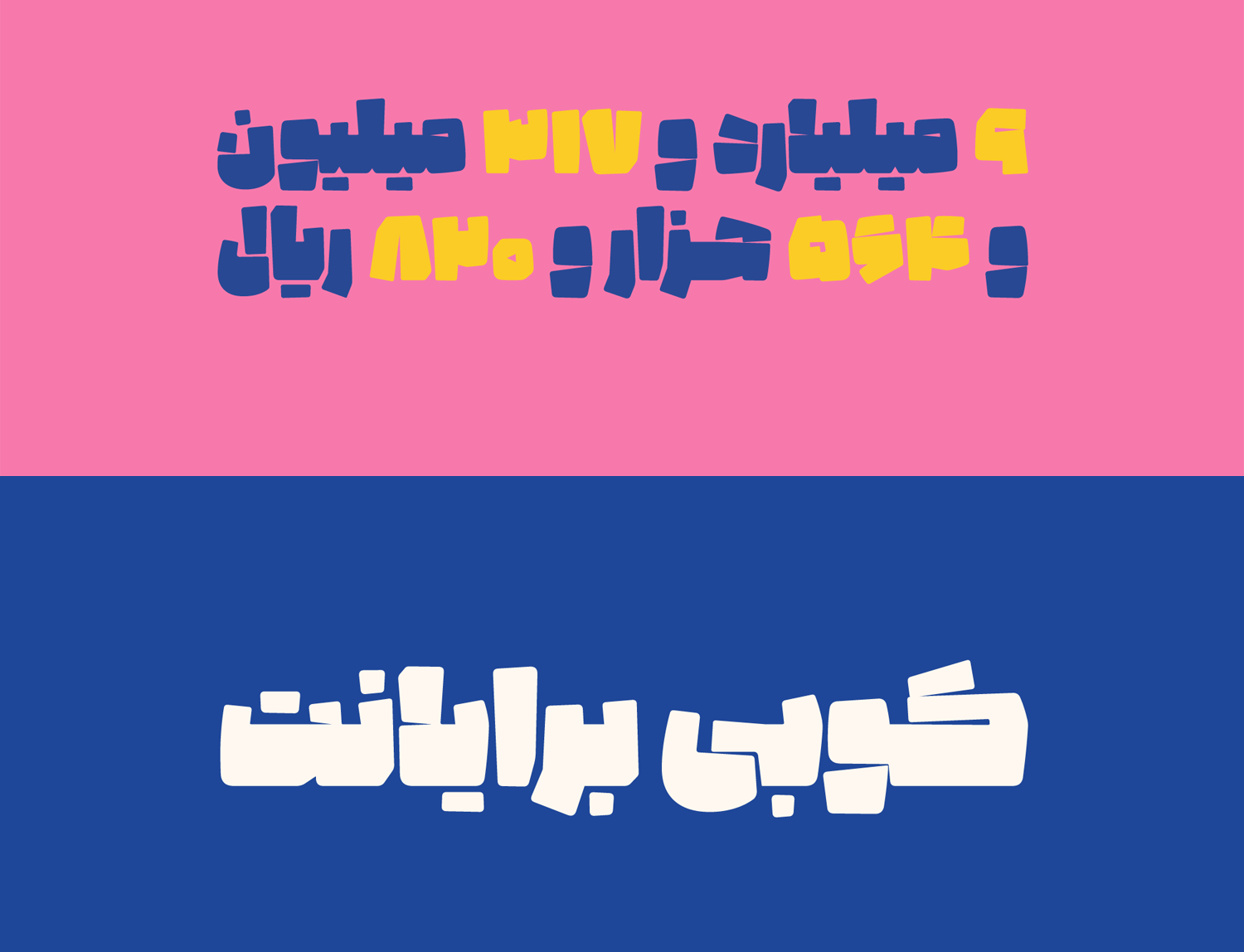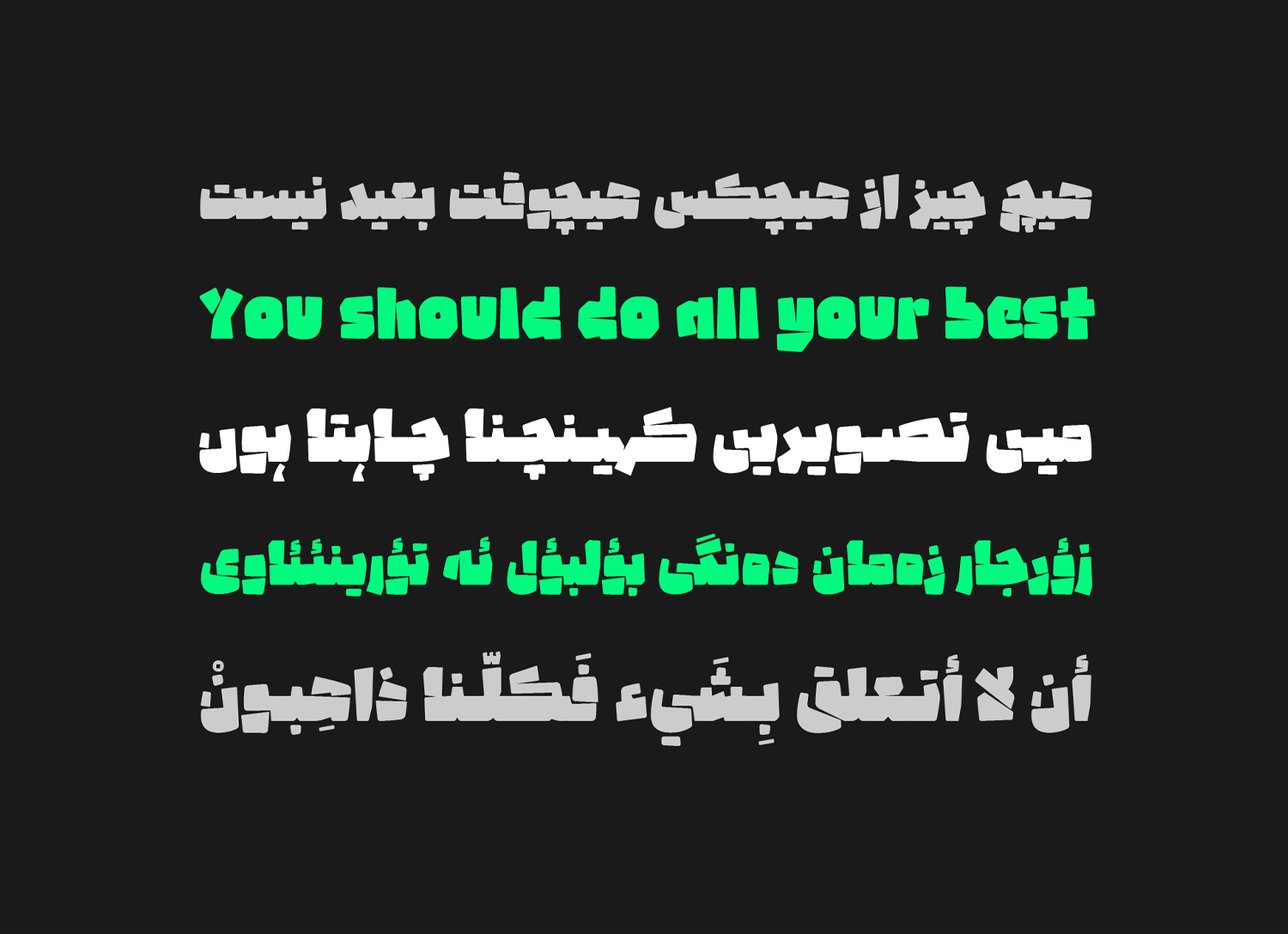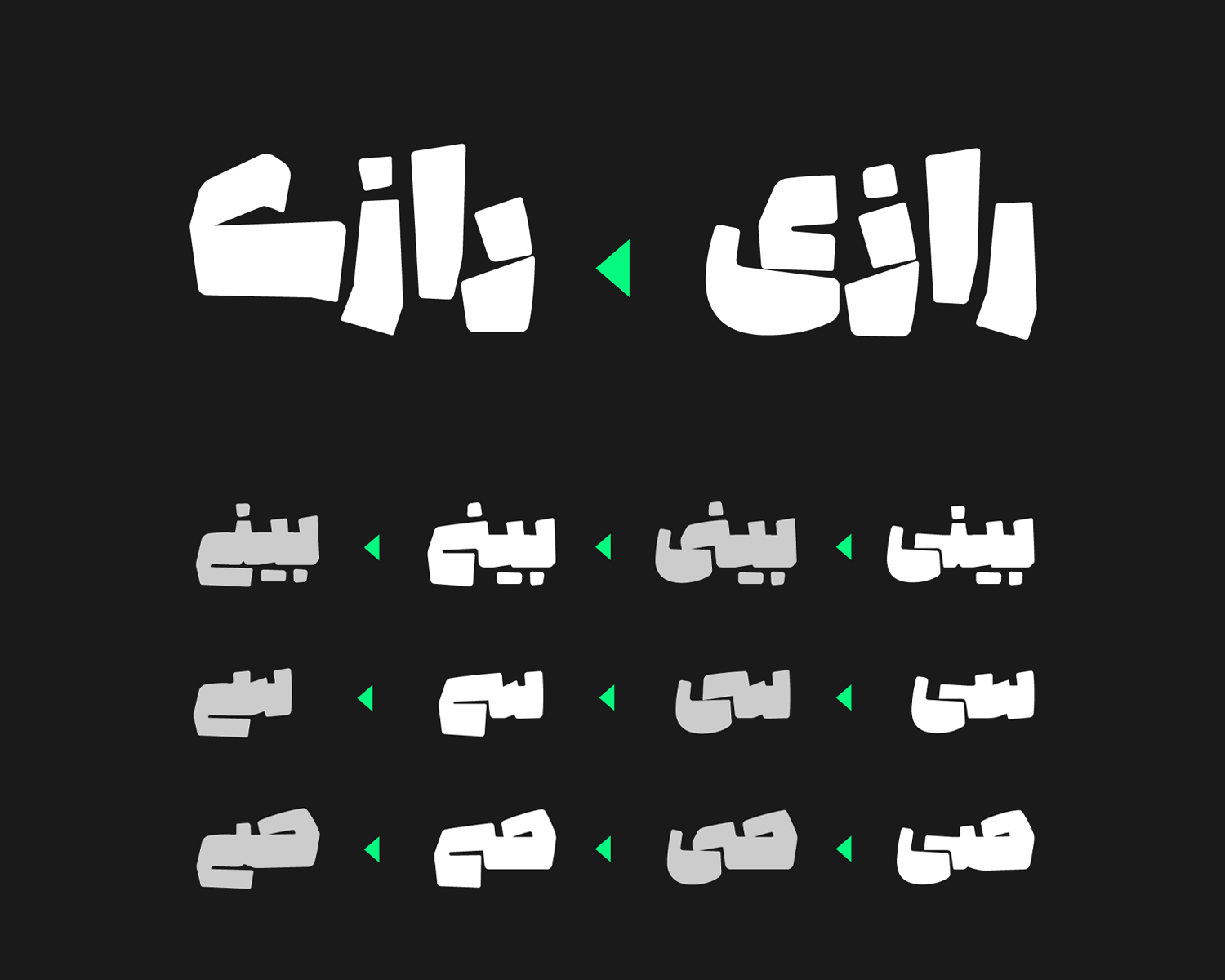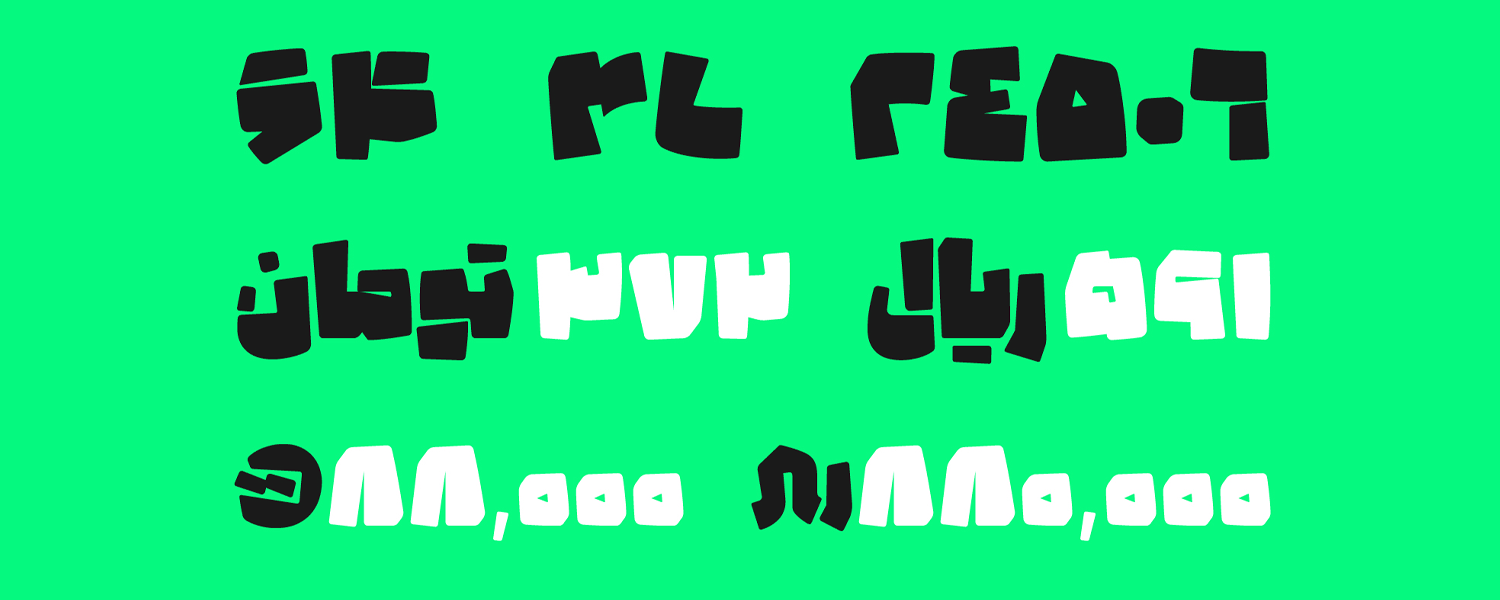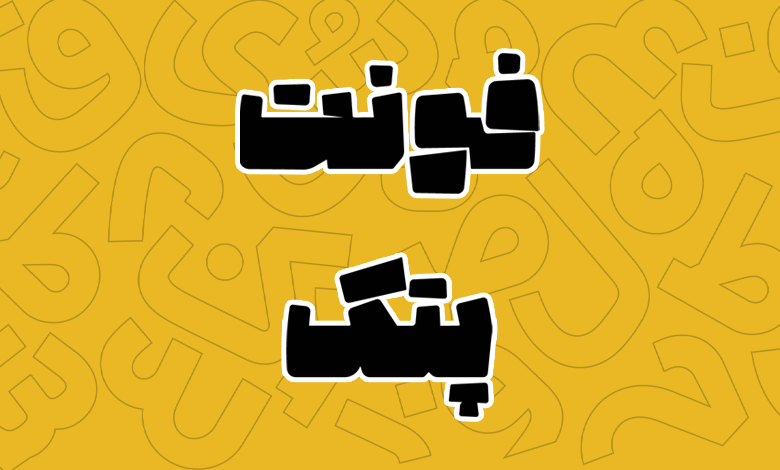
فونت پتک (Potk)
فونت پتک (به انگلیسی: Potk) در دنیای پر تلاطم خطوط فارسی، درست در جایی که نیاز به فونتی برای جلب توجه مخاطب داریم ظاهر شده است. این فونت فانتزی که از وزن سیاه (Black) پشتیبانی میکند، دارای ساختاری هندسی و نمایشی است که نهتنها برای عناوین کوتاه و تیترها کاربرد دارد، بلکه با الهام از ضربات قدرتمند پتک بر آهن گداخته، شکلی نو و خلاقانه به حروف میبخشد.
اگر به دنبال فونتی نمایشی و هندسی هستید که سیاهی حداکثری را در خود داشته باشد و در عینحال جلوهای فانتزی به حروف ببخشد از فونت پتک استفاده کنید. مهدی ارشادی این قلم را برای پروژههای گرافیکی جسورانه طراحی کرده است. فونت پتک رایگان نیست و در قالب یک وزن سیاه قابل خریداری است.
در ادامه این نوشته از فونتچی، به نقد و بررسی کامل فونت پتک خواهیم پرداخت؛ قلمی با وزن فوق سنگین و نمایشی که پیش از این نمونههای مشابه این قلم را در صفحات فونت صنعت و فونت تهمتن بررسی کردهایم.
بررسی و دانلود فونت پتک (Potk)
حروف فارسی را زیر ضربات بیرحم یک پتک، تصور کنید که تغییر شکل داده و هرکدام شخصیت خاص خود را میگیرند. در برخی لبهها از خوردگیهای پتک ظاهری نرم میگیرند، برخی دیگر طاقت ضربات را نداشته و با شکستگیها و شکافهای ناگهانی خود را نشان میدهند و برخی دیگر با فرورفتگیهای خاص خود، با تحمل ضربات خودنمایی میکنند.
فونت پتک دقیقا با چنین رویکردی ساخته شده است. ساختار هندسی آن، با کاهش فضای بین حروف (کرنینگ فشرده)، برهمزدن یکنواختی ضخامتها و تغییرات تصادفی در اندازهها، یک فونت فانتزی سنگین میسازد که برای عناوین کوتاه، عکس نوشتهها و لوگوتایپها بینظیر است.
در دنیای فونتها باید واقعبین باشیم؛ هیچ فونتی کامل نیست و این فونت هم مثل هر فونت دیگری برای استفاده در پاراگرافهای طولانی مناسب نیست. اما وقتی صحبت از تیترها، پوسترها، کاور آلبومها و استوریهای اینستاگرام به میان آید، مانند یک چکش بر آهن داغ عمل میکند.
وجود اعراب متناسب با جثههای متفاوت و نقطههای متمایز در حروف (مانند دو شکل جایگزین برای «ر»، «ک»، «ه» و «ه»)، جلوه نمایشی را تقویت میکند. وجود ترکیبات اختیاری و کشیدگیها (لیگاتورها) دست طراحان را برای خلق عباراتی کاملا سفارشی بازتر میکند. خلاقیت در جزئیات، مانند الهام از کوبیدن پتک بر سنگ یا سیمان، پتک را به یک ابزار هنری تبدیل کرده که هر بار استفاده، حس تازگی میدهد.
فونت کولاک و فونت بلوک از دیگر قلمهای طراحی شده با همین سبک هستند که وزن فوق سنگین و ضخامت زیادی دارند. از این قلمها میتوانید برای طراحی در تبلیغات استفاده کنید که خصوصا نیاز است نامی از برند برده شود.
یا اینکه با توجه به ساختار قلم که الهام گرفته از آهن و آهنگری است، در طراحی تابلوهای صنعتی در سردر فروشگاهها، کارگاهها و هر واحدی که محصول یا خدماتی دارد که قدرت و مقاومت جزو ارکان اصلی آن است استفاده کنید.
ویژگیهای فنی و وزن فونت پتک
فونت پتک در یک وزن سنگین ساخته شده، که با سیاهی حداکثریاش، برای فونت سنگین سیاه فارسی ایدهآل است. پشتیبانی از زبانهای فارسی، عربی، کردی، اردو و انگلیسی، آن را به گزینهای مناسب برای کارهای چندزبانه تبدیل کرده است. خصوصا در موضوعات تبلیغاتی که بیشتر کاربرد دارد. این فونت با پشتیبانی از اعداد فارسی و حروف جایگزین (Alternates) امکان خلق بهتر کارهای گرافیکی را فراهم کرده است.
در طراحی کلیه حروف با ضخامتی متغیر مواجه هستیم که در اثر ضربات پتک ایجاد شده و انتظار هم میرود برخی حروف شاهد خطوطی صاف و در برخی دیگر شاهد خطوط مورب باشیم که در اثر این ضربات وارد شدهاند.
کوبیدن پُتک روی هر چیز به تغییر ریخت اجسام میانجامد و با داشتن ایدهای مناسب میتوان آن را به شکلی خاص بدل کرد. تفاوتی نمیکند چه چیز زیر ضربات پُتک قرار دارد؛ نحوهی برخورد و شدت ضربهها تعیین کننده است. آهن گداخته، سنگ معادن، بلوکهای سیمانی و حتی حروف قابلیت تغییر شکل دارند.
مهدی ارشادی؛ طراح قلم پتک.
این قلم فقط دارای یک وزن سیاه Black است؛ اما با این حال ضخامتی که حروف دارند سیاهتر به نظر میرسند. هرچه هم سایز فونت را درشتتر کنید، با توجه به ترکها، نرمی و شکافها، بیشتر دیده شده و جلب توجه خواهند کرد.
پشتیبانی از ۵ زبان مختلف
فونت فارسی پتک محدود به این زبان نیست و با زمانی که روی طراحی و توسعه آن با دید آهنگری صرف شده، توسعه دهنده صبر زیادی را به خرج داده تا نتیجه نهایی را در قالب ۵ زبان مختلف در اختیار داشته باشید.
عربی، انگلیسی، اردو و کردی از دیگر زبانهای پشتیبانی شده هستند. ساختار هر زبان به شکل استاندارد پیادهسازی شده است. بهطوری که اعراب و کاراکترهای تزئینی در همنشینی استانداردی با حروف قرار دارند. علاوهبر این حروف جایگزین، برای زبانهای برپایه رسمخط فارسی قابل استفاده است.
تغییراتی مثل کمشدن فضای بین حروف و چشمیها، برهمزدن یکنواختی در ضخامتها، شکستگیهای اتفاقی در اثر ضربات پتک و تغییر در اندازهها فضای متفاوتی را در فونت پتک برای تمامی زبانها بهوجود آورده است که با دقت به تصویر بالا میتوان این موضوع را هم متوجه شد.
ترکیبات و حروف جایگزین متنوع
ویژگی متمایز کننده دیگر این قلم پشتیبانی از حروف جایگزین متعدد و برخی ترکیبات است که امکان تایپ کلمات را بر اساس شکل متفاوتی از حروف و نقطهها فراهم نموده است که ساختاری نمایشیتر به قلم میدهند.
وجود ترکیبهای متنوع در فونتهای نمایشی برای خلق کلمات متفاوت امری لازم است؛ چرا که ارائه این ترکیبهای جایگزین و از پیش تعیینشده برای طراحان کاربردی خواهد بود.
برای نمونه در این قلم میتوانید دو حروف رایج «ک، گ» را با توجه به اینکه جدا بوده یا با اتصال به سایر حروف در ابتدا یا میانه کلمات استفاده شده باشند، در چند حالت مختلف زیر در اختیار داشته باشید.